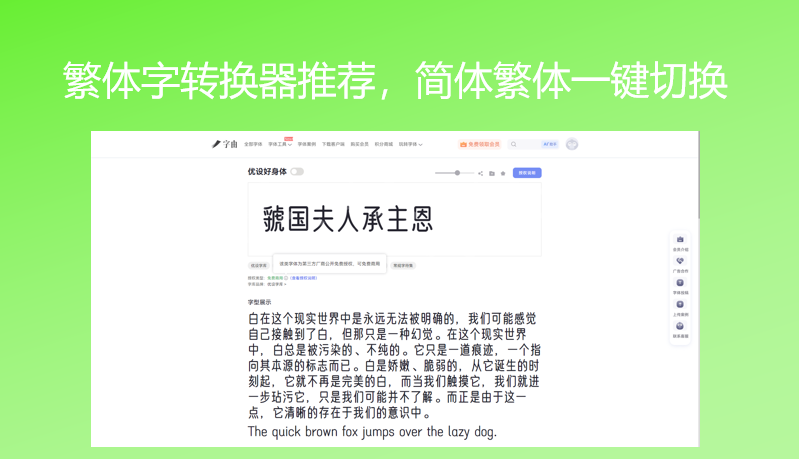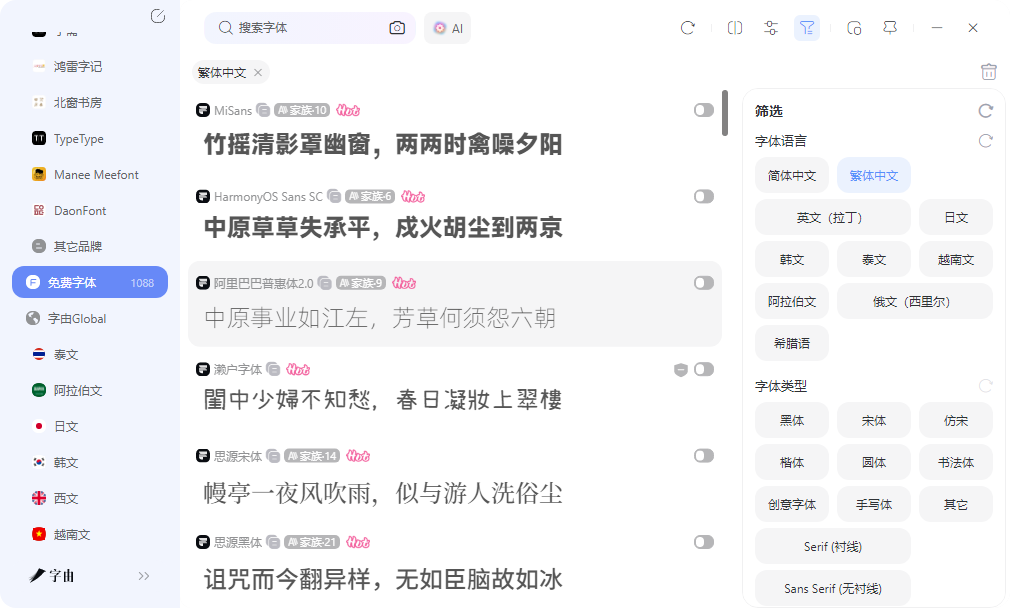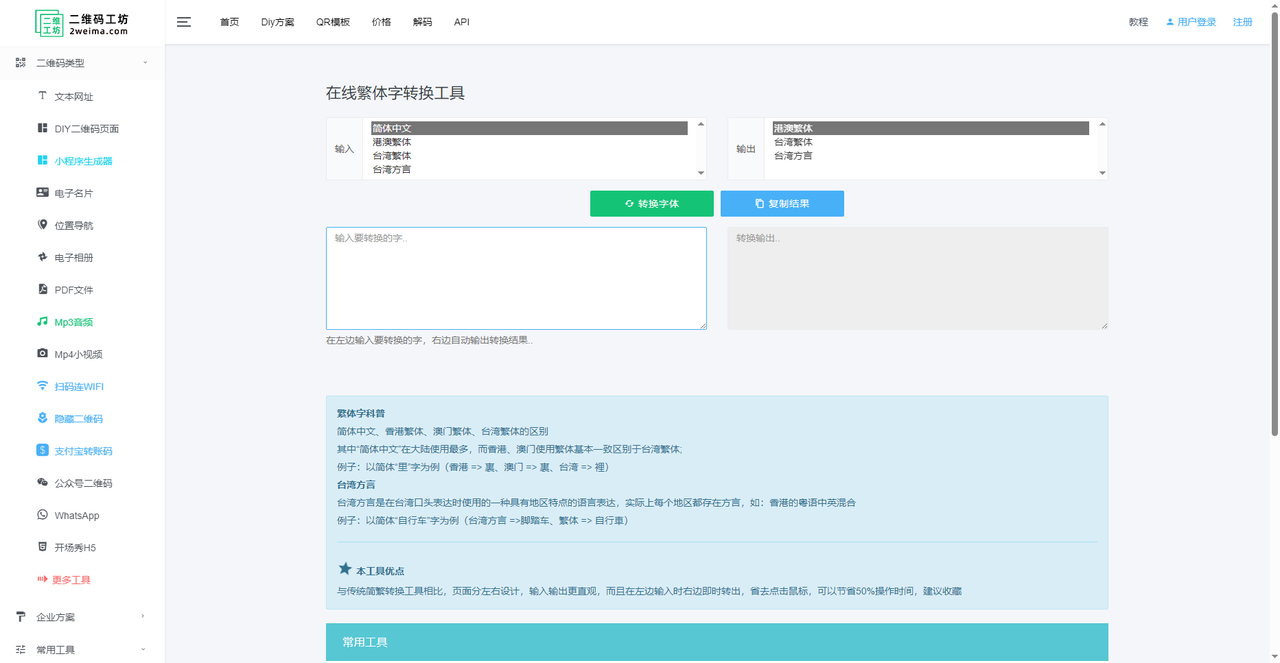
繁体字转换器推荐,简体繁体一键切换
做港台市场物料或者古籍排版时,繁体字是刚需。但繁体字转换不只是把简体文案贴进转换框里点一下按钮这么简单,后续设计环节里字体支不支持繁体字符集才是更大的坑。很多中文字体只做了简体常用字适配,遇到"國""龍""龜"这类繁体字形直接显示为默认宋体或者方框,整套设计稿的气质瞬间崩掉。这篇文章整理的五个渠道,从纯文本转换到繁体字体资源获取都有涉及。
字由在繁体字设计场景下的价值,在于提供了不少原生支持繁体中文的字体资源。台湾和香港的字体厂商在入驻平台时,通常会把繁体字符集做完整,比如jf open 粉圆、台北黑体等,这些字体在繁体文案下的显示效果比简体字体强行渲染要自然得多。简体字体遇到繁体字形时,往往是用默认字形回退,笔画粗细和风格完全不搭,放在海报里一眼就能看出来。
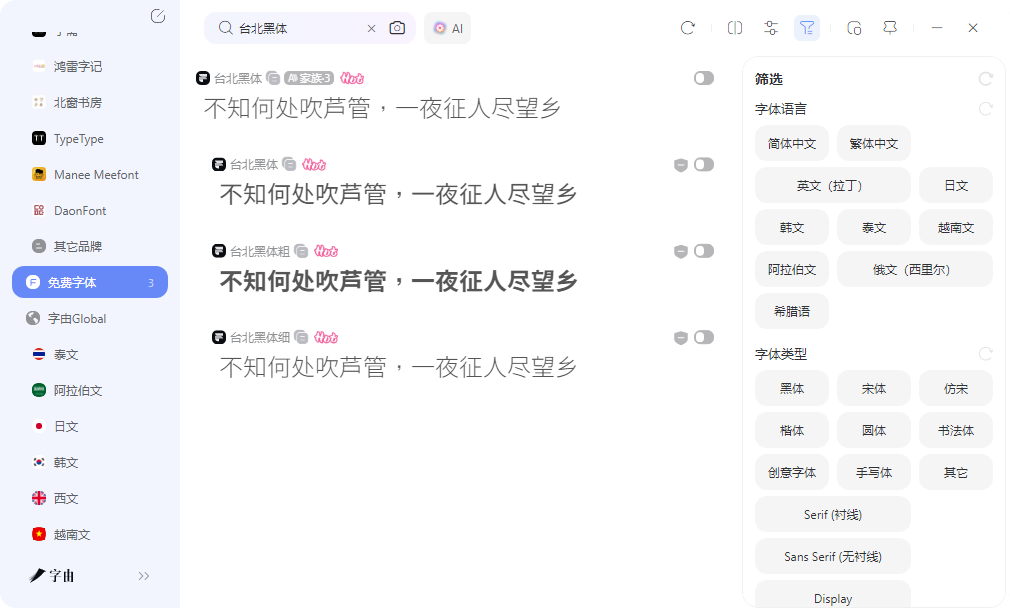
找繁体字体时,字由的筛选机制比较实用。网页版的筛选栏在页面顶部,客户端的筛选在右侧,都可以按书体类型和风格标签交叉过滤。需要特别注意的是字符集标注,每款字体的详情页会显示支持的字符范围,确认是否覆盖了繁体中文常用字区。有些字体虽然名字里带"繁体"或者"台湾",但实际只覆盖了一部分常用字,遇到生僻繁体字还是会缺字。详情页的字符集数据能帮你在激活前排除这类风险。
预览环节对繁体字尤其重要。同一款字体在简体和繁体下的视觉感受可能完全不同。简体字形结构相对简单,笔画少,字体设计师容易做出精致感;繁体字形结构复杂,笔画多,同样的字重下可能显得拥挤。字由的预览支持输入繁体文案,比如"臺灣設計師協會"或者"香港品牌視覺識別手冊",调整到实际使用字号后观察笔画密度和留白是否舒适。有些字体在24pt以下清晰度不错,放大到标题字号后繁体笔画开始粘连,这些细节在预览环节能提前发现。
收藏分组功能对繁体项目管理比较实用。可以把港台项目常用的几款繁体字体归到一个分组里,命名成项目代号或者客户名称。下次做同类项目时直接打开分组调用,不需要重新搜索。分组里的字体都经过字符集确认,商用授权信息也一并保留,交付时导出字体文件发给客户或者印刷厂,对方打开源文件不会丢失字体。
2、免费在线繁体字转换工具
免费在线繁体字转换工具支持文档级别的转换,可以保留原文的段落格式、标点符号和特殊符号。用户粘贴大段文字后,转换结果的排版结构和原文基本一致,不需要重新调整。
作为繁体字转换器,它的优势在于格式稳定性。有些工具转换后会把所有文字挤成一段,或者丢失换行和缩进,这里能较好地保留原始排版。对于需要转换长篇文章、报告或者合同文本,且对格式有一定要求的场景来说,这里的输出比较省心。转换结果可以直接复制使用,也可以手动下载保存。
3、即时工具简体转繁体
即时工具的简体转繁体支持多种转换模式,包括台湾标准和香港标准。这两个地区虽然都用繁体中文,但部分用词和字形有差异,比如"軟體"和"軟件"、"設定"和"設置"。选择对应的标准后,转换结果会更贴合当地用语习惯。作为繁体字转换器,它的优势在于标准细分。做台湾市场物料时选台湾标准,做香港市场时选香港标准,转换后的文案本地感更强,不需要大量后期人工校对。对于需要精准匹配当地语言习惯、而不是简单做字形转换的项目来说,这里的多标准支持比较实用。工具还支持批量处理和格式保留,转换后的段落结构不会乱。
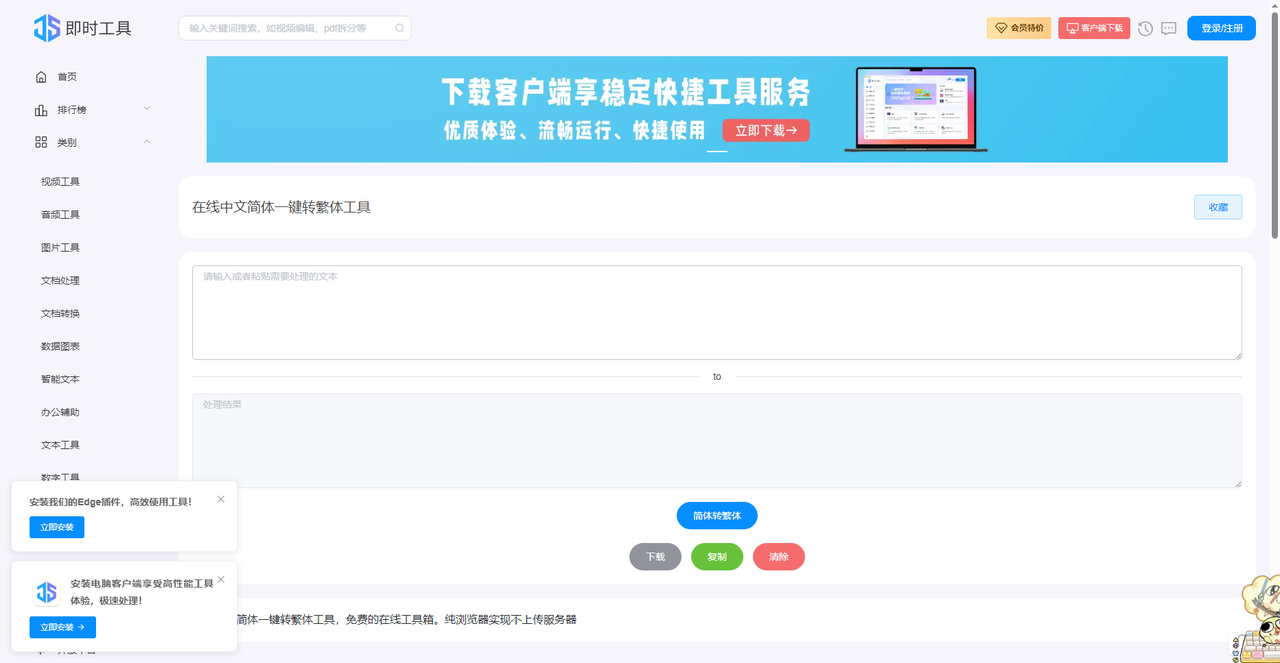
4、繁体转简体在线转换
繁体转简体在线转换支持双向切换,既可以简体转繁体,也可以繁体转简体。这个特性对处理混合文档比较实用,比如收到一份台湾同事发来的繁体Word文档,需要转换成简体后再编辑,或者把自己的简体报告转换成繁体版本发给香港客户。
作为繁体字转换器,它的优势在于方向灵活。有些工具只做单向转换,遇到反向需求时得另找工具,这里一个页面解决两个问题。转换结果支持直接复制,也可以下载为TXT文本文件。对于需要频繁在简繁之间切换、且希望同一个工具搞定双向需求的人来说,这里的便利性比较高。
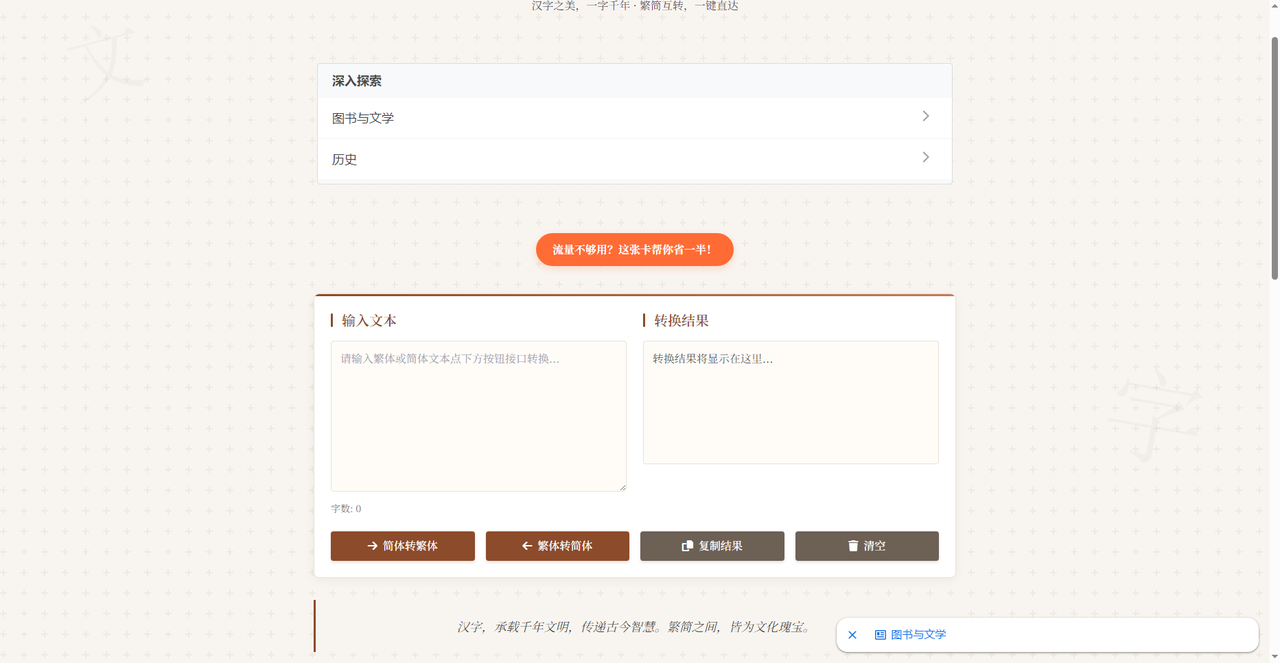
5、技艺工具繁体字转换器
技艺工具的繁体字转换器是一个纯文本转换工具,界面比较简洁。用户在输入框里粘贴简体文案,点击转换按钮后,系统会输出对应的繁体中文文本。支持批量转换,一次可以处理大段文字,不需要逐句复制粘贴。
这个工具对需要快速获得繁体文案初稿的场景比较实用。做港台社交媒体运营时,把简体推文批量转换成繁体,再人工校对一遍台湾用语习惯,效率比逐字手打高很多。作为繁体字转换器,它的优势在于操作极简,没有多余功能干扰,打开网页就能用。转换结果可以直接复制到剪贴板,粘贴到设计软件或者文档编辑器里继续排版。
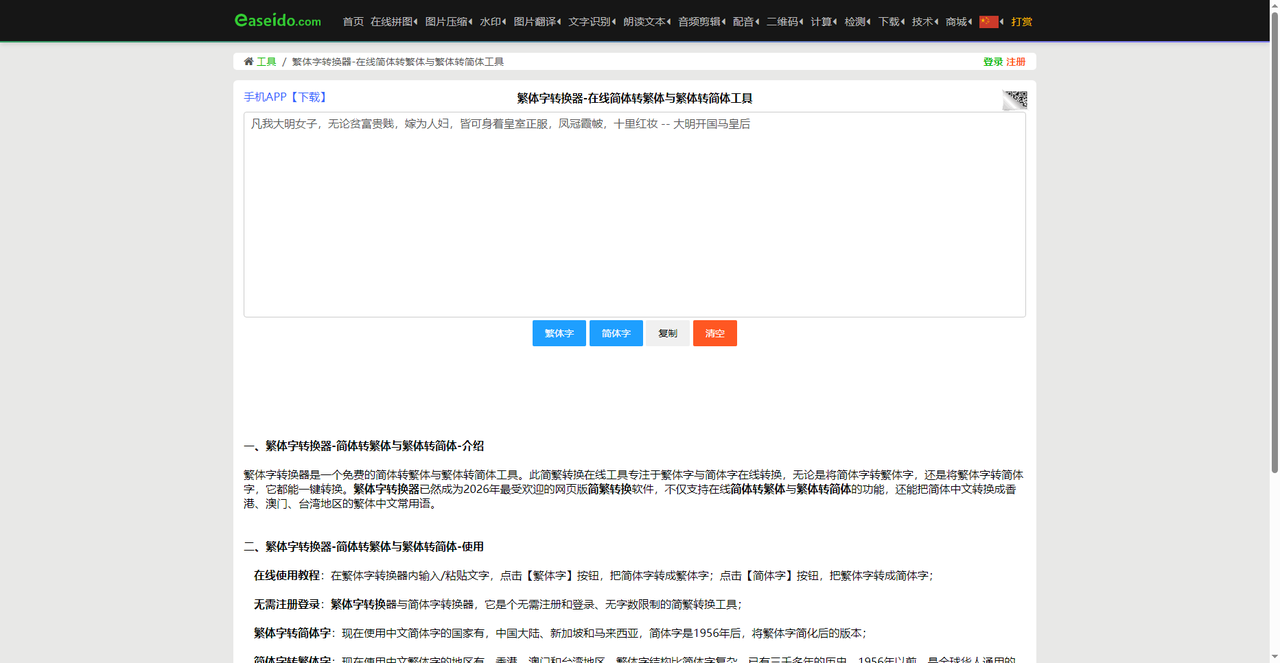
先把简体文案用繁体字转换器转成繁体,再到字由里确认字体是否支持繁体字符集,预览繁体文案的实际显示效果,整套流程下来出错的概率会降低不少。技艺工具适合快速批量转换初稿,繁体转简体在线转换支持双向切换比较灵活,即时工具的多标准转换对精准本地化比较实用,免费在线工具的格式保留对长文档比较友好。字由则负责后续设计环节的字体资源确认和项目管理。前后环节搭配起来,简繁切换这件事就方便多了。